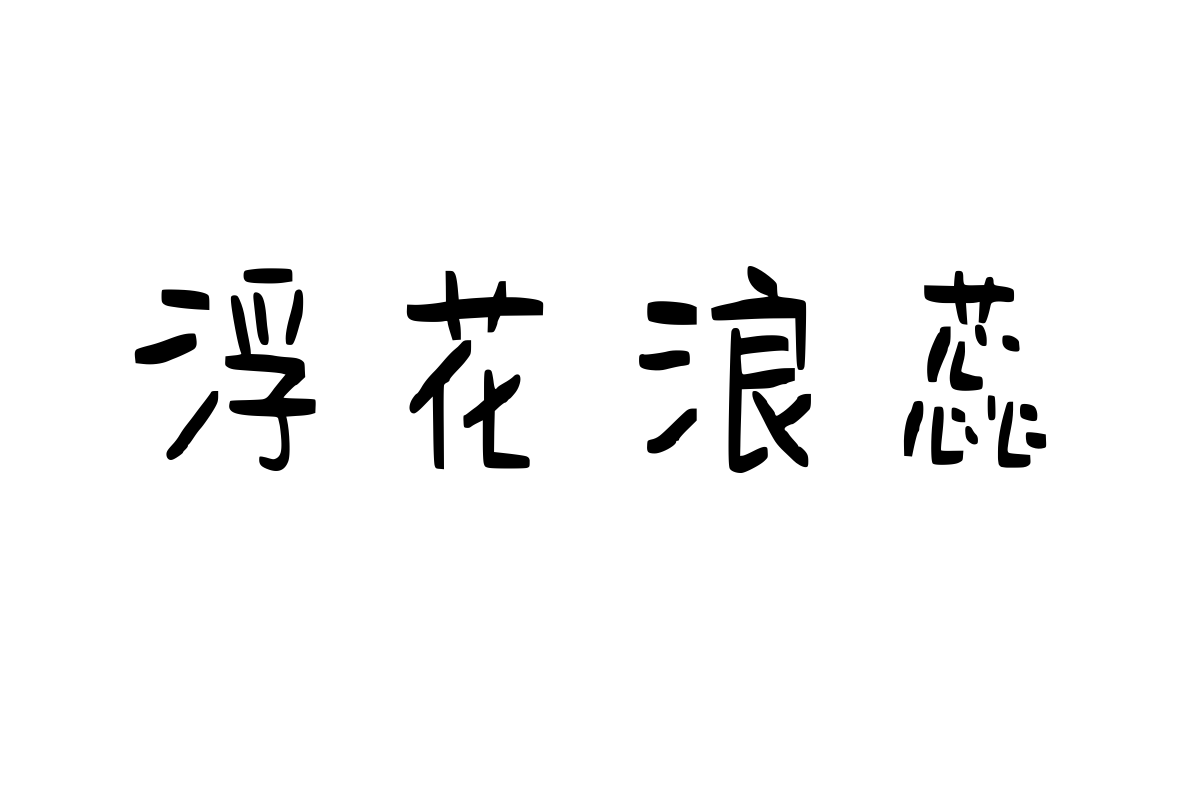
兰米自然萌字体是一款现代、简洁的中文字体,具有独特的风格和特点。它采用了柔和的线条和流畅的笔画,给人一种轻松、愉悦的感觉。这种字体非常适合用于儿童读物、儿童游戏、儿童插画等场景,能够吸引孩子们的注意力,激发他们的想象力和创造力。
兰米自然萌字体的特点是:
1. 线条流畅,笔画圆润,给人一种舒适、亲切的感觉。
2. 字形简洁明了,易于阅读和理解。
3. 适合用于儿童读物、儿童游戏、儿童插画等场景,能够吸引孩子们的注意力,激发他们的想象力和创造力。
4. 具有一定的可读性和美观性,适用于各种印刷媒体,如书籍、杂志、海报、广告等。